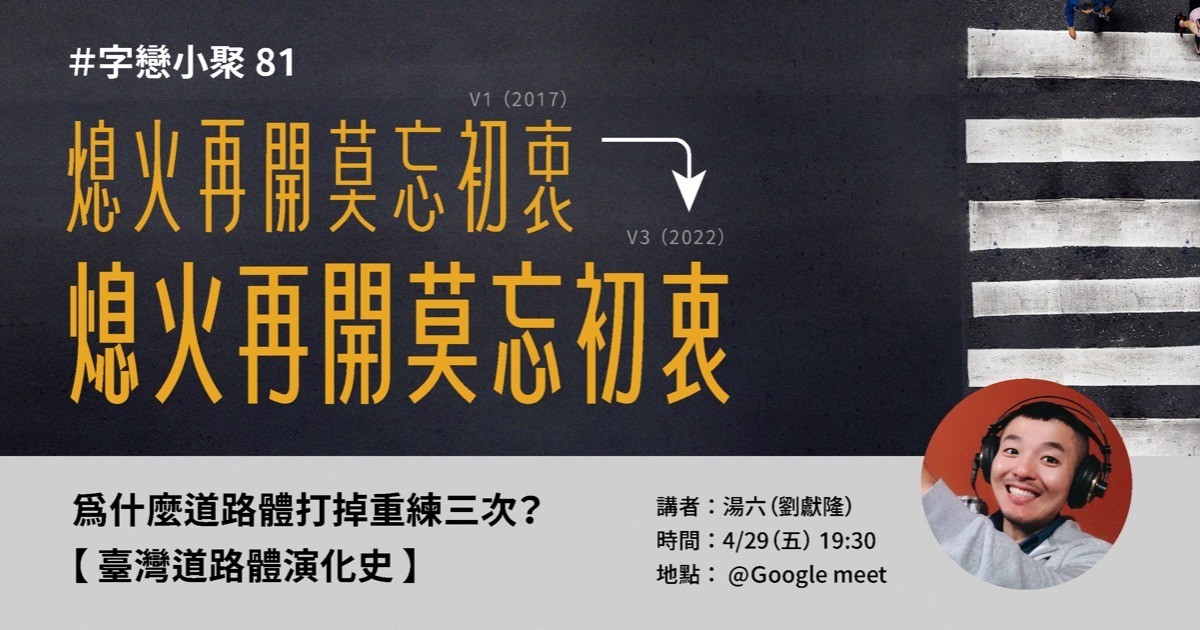
字戀小聚 #81|為什麼道路體打掉重練三次? 【臺灣道路體演化史】
2017 年臺灣道路體問世引發話題,設計師湯六原先以為只要順勢完成便可推出,但在許多設計合作以後,卻收到「道路體不太好用」的回饋。問題出在哪裡呢?
原來是第一版以等寬線條復刻馬路文字的道路體,並不符合我們習慣的漢字美學,所以讓人覺得「不太像字」,怪怪的。湯六經過一番學習、磨練與修改,煞費苦心更新至第三版,現在的臺灣道路體才終於成為完整好用的字型產品。究竟何謂漢字美學?初代道路體與正式版的差異有哪些?就讓已經練就一身功力的湯六現身說法,一一為你解析!